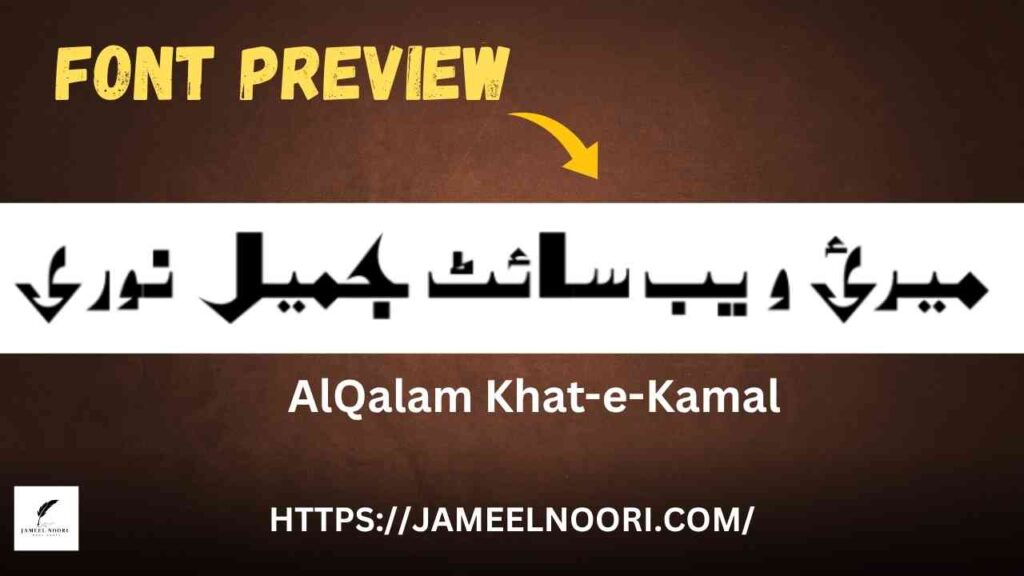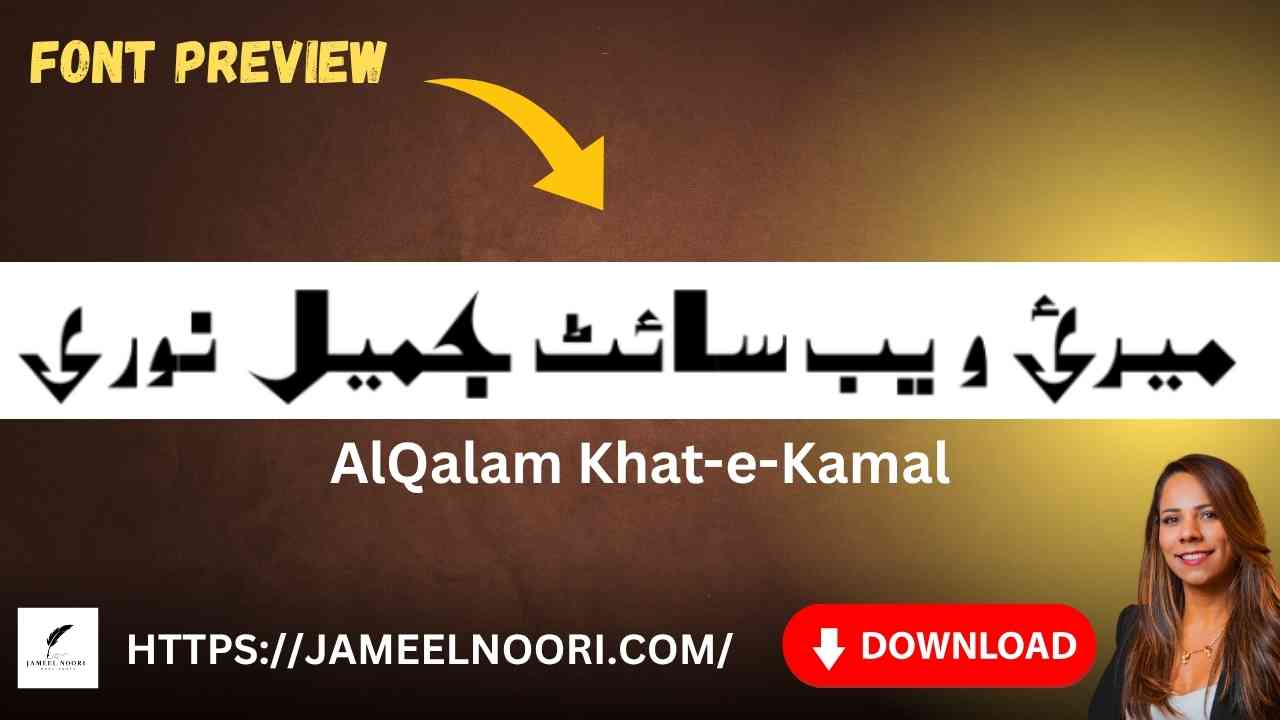
Introduction – Urdu Font AlQalam Khat-e-Kamal Ko Pehle Jaaniye
Urdu Font AlQalam Khat-e-Kamal Pakistan ke designers aur writers ke liye aik ultimate choice hai. Ye font clean aur elegant style me available hai, jo har type ki digital aur print design me perfect lagta hai.
Features of Urdu Font AlQalam Khat-e-Kamal
Urdu Font AlQalam Khat-e-Kamal ke features designers aur students dono ke liye highly beneficial hain. Is font ke key features ye hain:
- Elegant Calligraphy Style: Professional aur readable Urdu text ke liye best.
AlQalam Khat-e-Kamal Regular – Character Map & Style
| Character Type | Style | Availability |
|---|---|---|
| Uppercase | Elegant Calligraphy | All standard Urdu characters |
| Lowercase | Smooth & Readable | Complete support for ligatures |
| Numbers | Stylish & Clear | 0-9 included |
| Symbols | Artistic & Simple | Urdu punctuation supported |
Ye font creative projects, blogs aur social media posts me use karne ke liye ideal hai.
Why Choose Urdu Font AlQalam Khat-e-Kamal in Pakistan
- Popular Choice in Lahore & Karachi: Designers aur students dono is font ko prefer karte hain.
- Professional Look: Har project me classy aur modern feel deta hai.
- High Compatibility: Digital aur print media dono ke liye best.